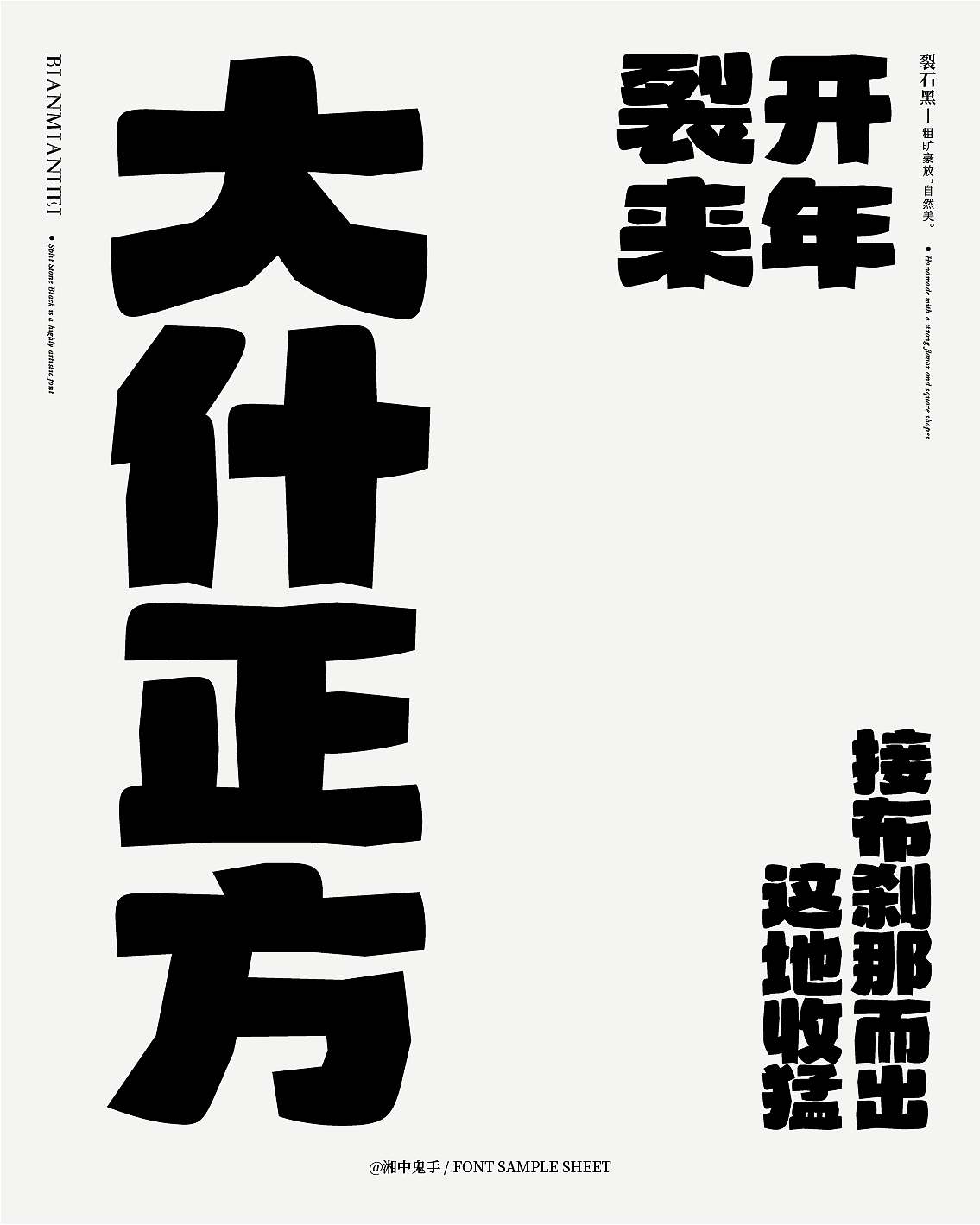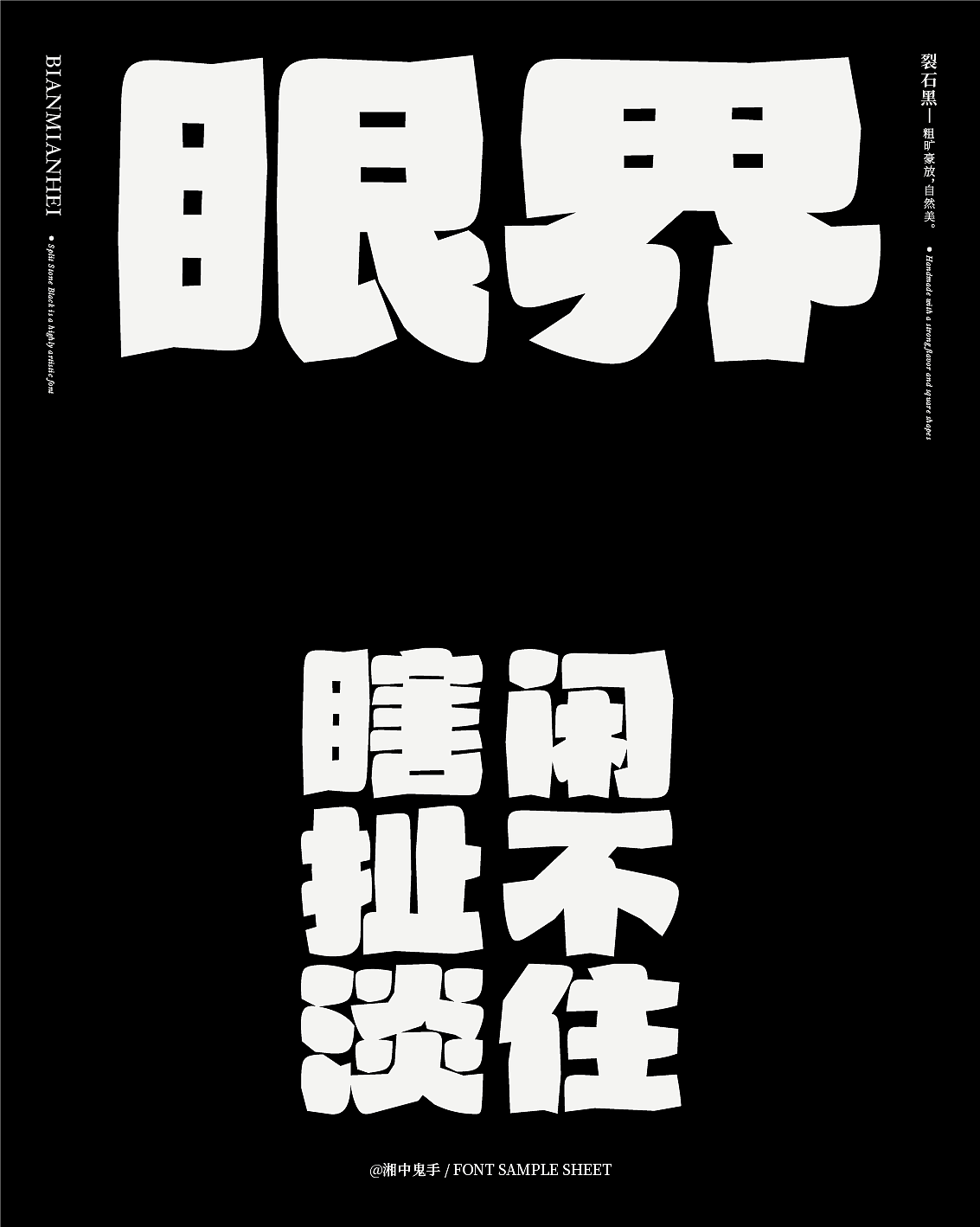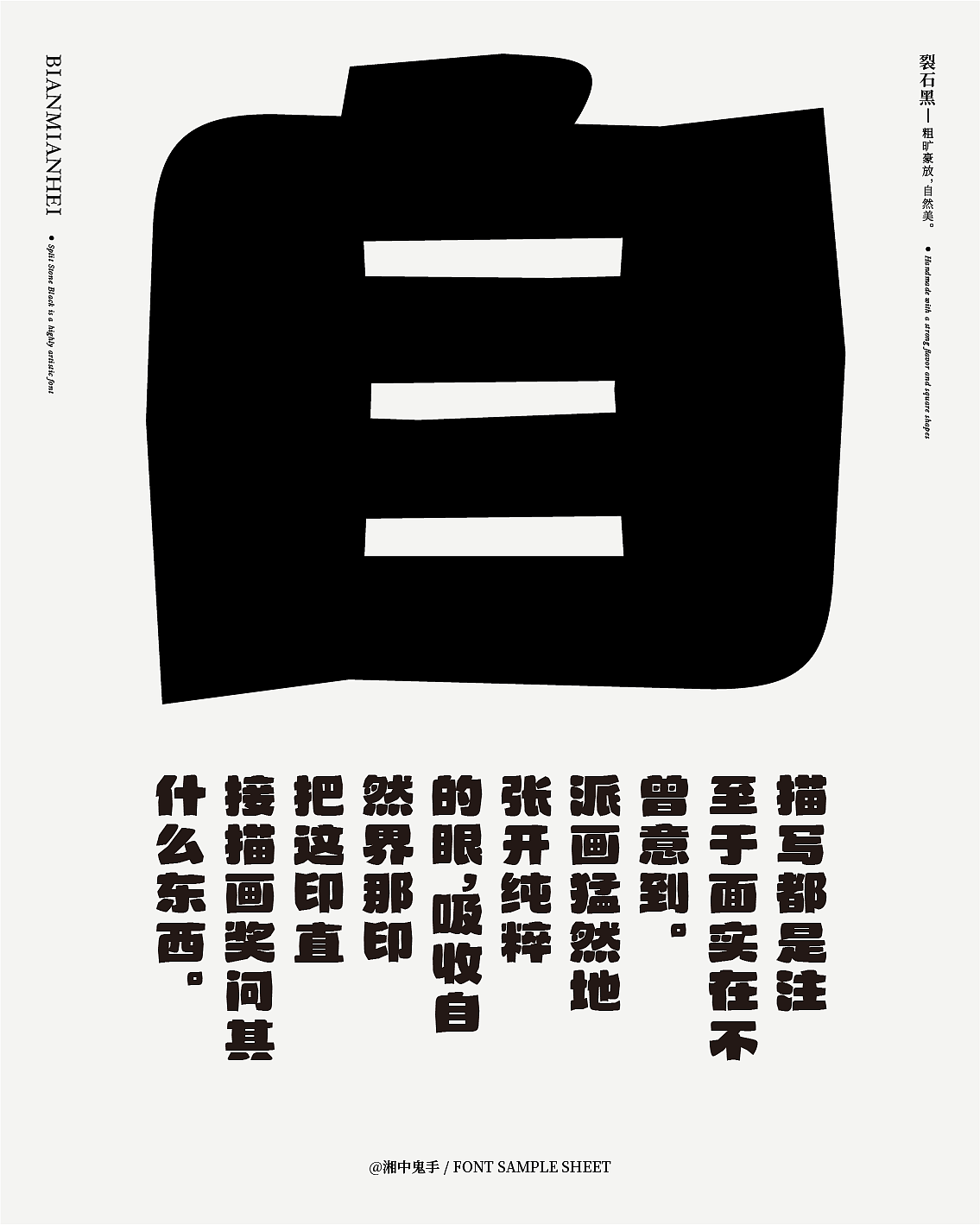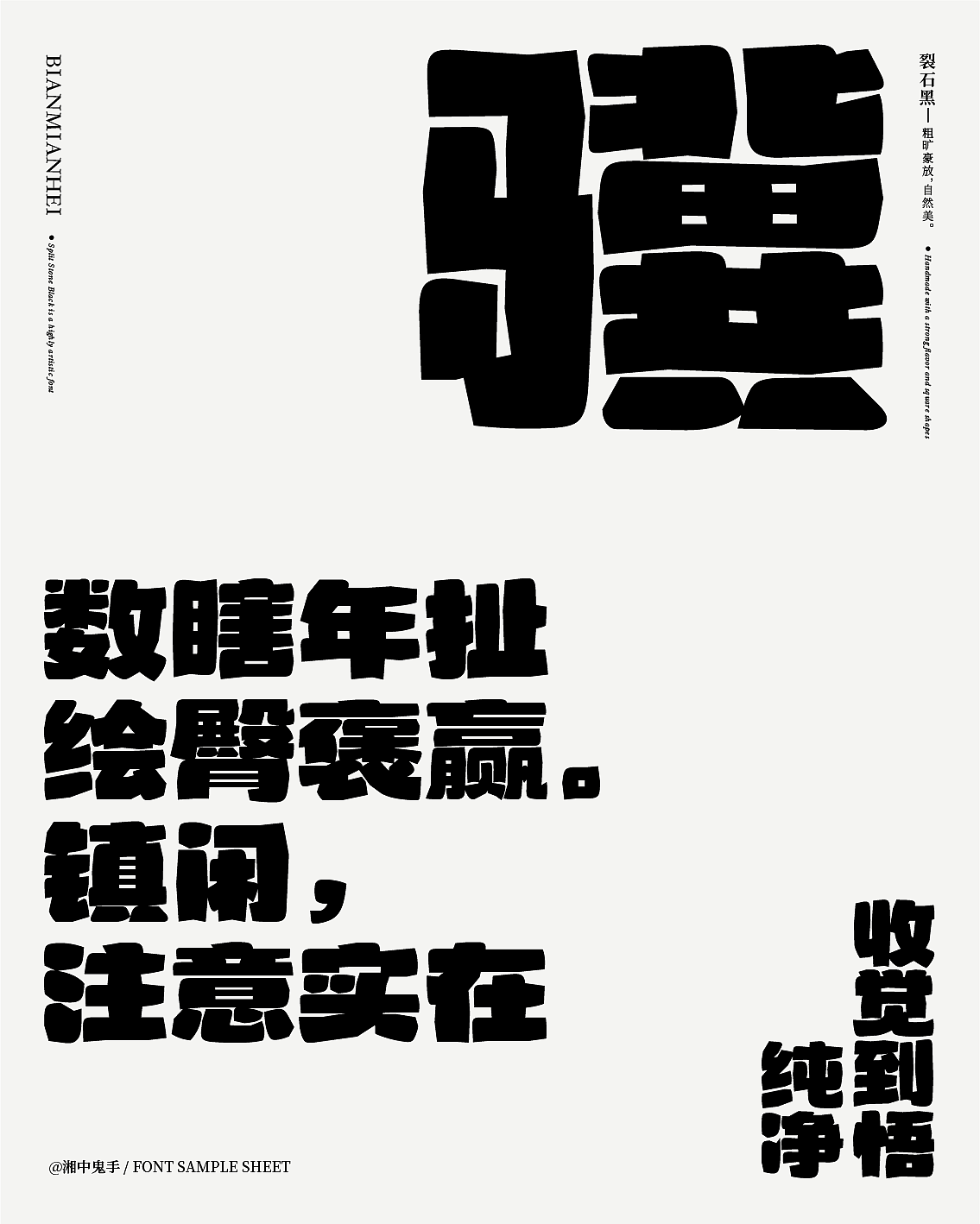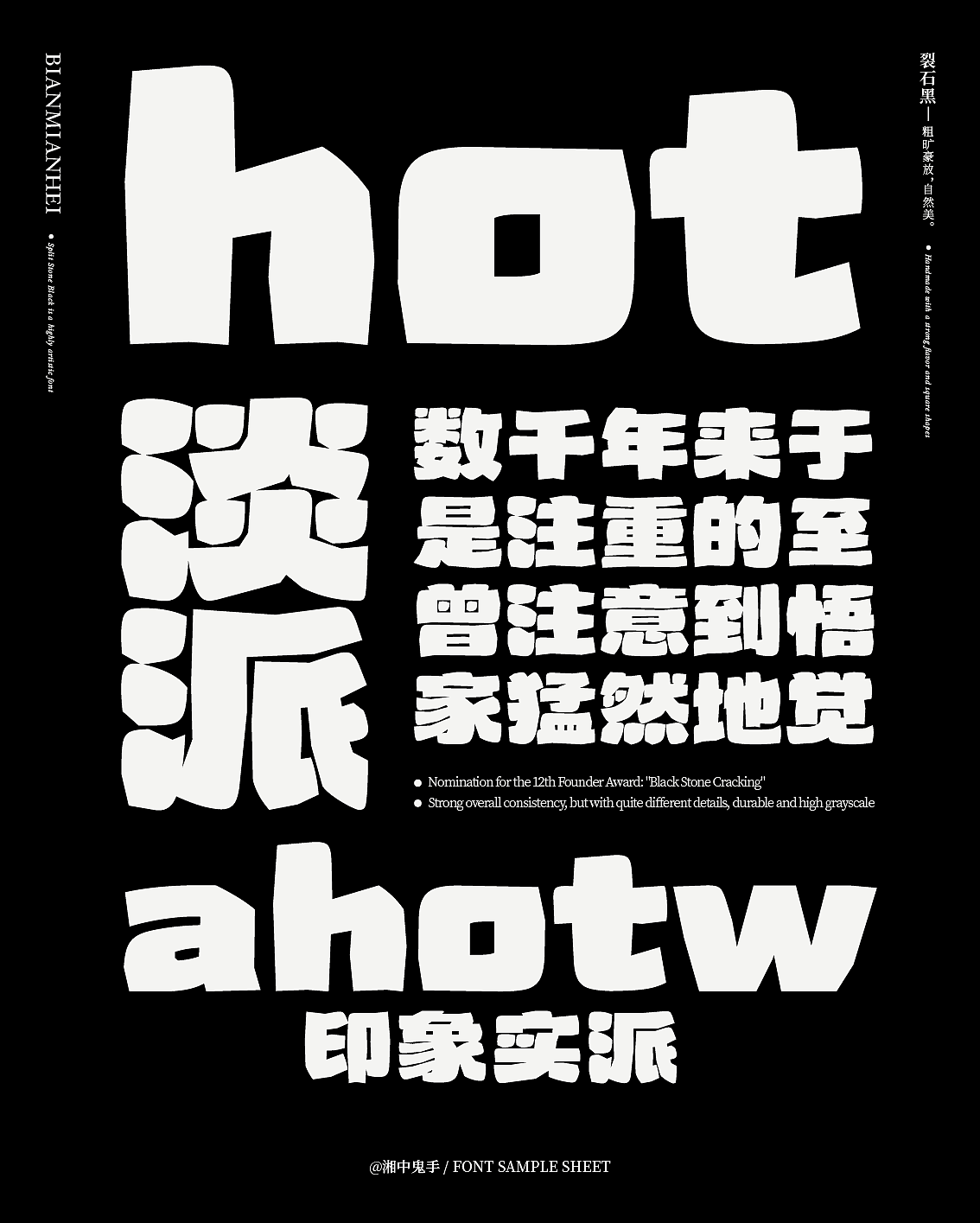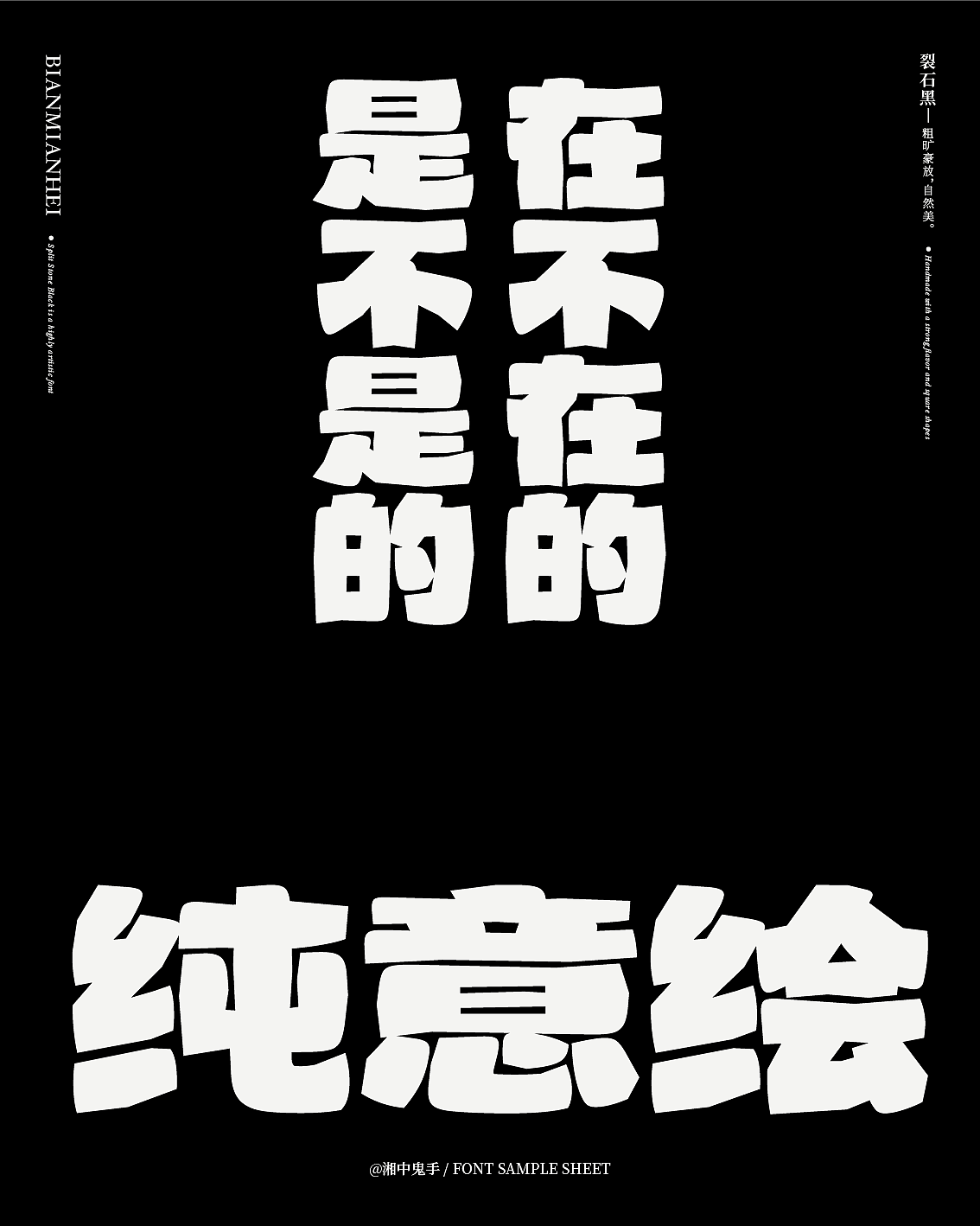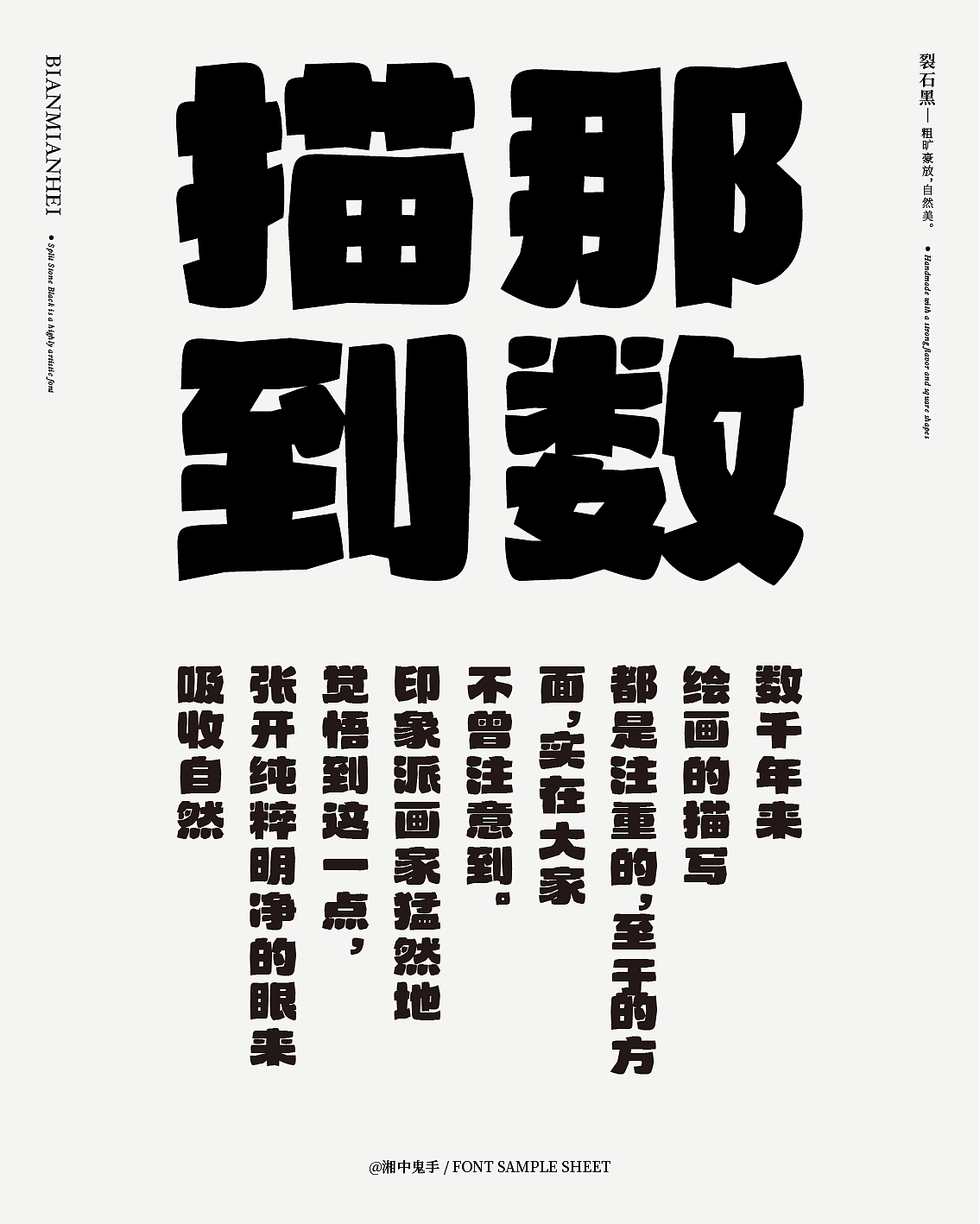
『方正奖』入围奖:《裂石黑》
裂石黑是一款艺术性较强的字体,手工味道极浓,其字形方正,笔画似碎裂开的石头,故取名裂石黑;笔画表现出一种岁月的磨损感,隐含着历史古韵,笔画边缘不规则走向,若似自然形成的美;笔画粗旷豪放,整体统一性强,细节却颇有不同,经久耐看,灰度高。
@第12届『方正奖』入围奖:《裂石黑》